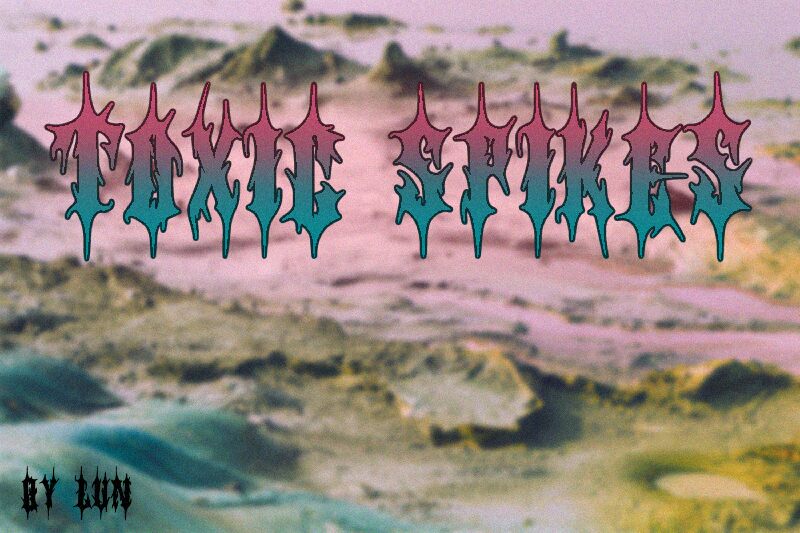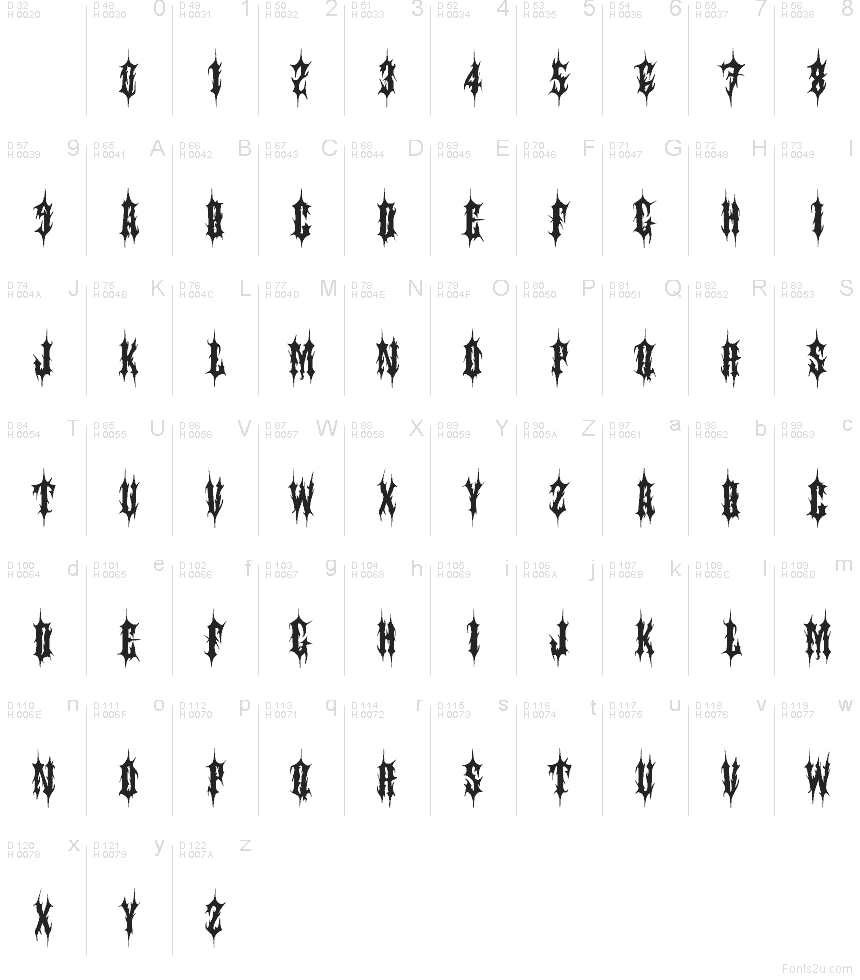
Toxic Spikes di LuN è un font display gotico gratuito con forme affilate e punte acuminate dai bordi irregolari e gocciolanti, che donano a ogni lettera un contorno grezzo e aggressivo. Le punte ripetute e i tagli frastagliati conferiscono ai caratteri un aspetto graffiato, con un'estetica horror dark che punta tutto sull'ornamento piuttosto che sulla struttura.
Toxic Spikes è un font gratuito ideale per locandine horror, copertine di album metal, titoli di giochi, volantini di eventi e grafiche per Halloween, poiché le forme fratturate trasmettono immediatamente un forte carattere usurato. È perfetto anche per logotipi, adesivi e titoli decorativi d'impatto, dove vuoi che il testo appaia ostile e instabile.